WELCHE ROLLE SPIELEN SCHRIFTEN FÜR DIE WIRKUNG EINER VERPACKUNG?
Es geht nicht nur ums Kleingedruckte! Logos, Bilder, Formen und Farben auf Verpackungen wie Faltschachteln, Versandkarton oder Doypacks, erregen den Großteil der Aufmerksamkeit. Sie springen ins Auge, werden wiedererkannt, wecken Emotionen.
Bei so viel visueller Schlagkraft rückt die Schrift im Verpackungsdesign manchmal in den Hintergrund. Dabei übernimmt sie nicht nur wichtige Aufgaben, sondern ist sogar integraler Bestandteil des Designs.
Bei der richtigen Typografie für eine Verpackung geht es deshalb nicht nur darum, wie sich alle wichtigen und geforderten Informationen auf der verfügbaren Fläche unterbringen lassen. Vielmehr gilt es herauszufinden, wie verschiedene Schriftarten wirken, was sie über dich und deine Marke aussagen, wie gut sie dazu passen und wie sie sich am besten in die Gesamtkomposition einfügen.
Wir erklären dir die grundlegenden Merkmale, auf die du dabei achten musst.
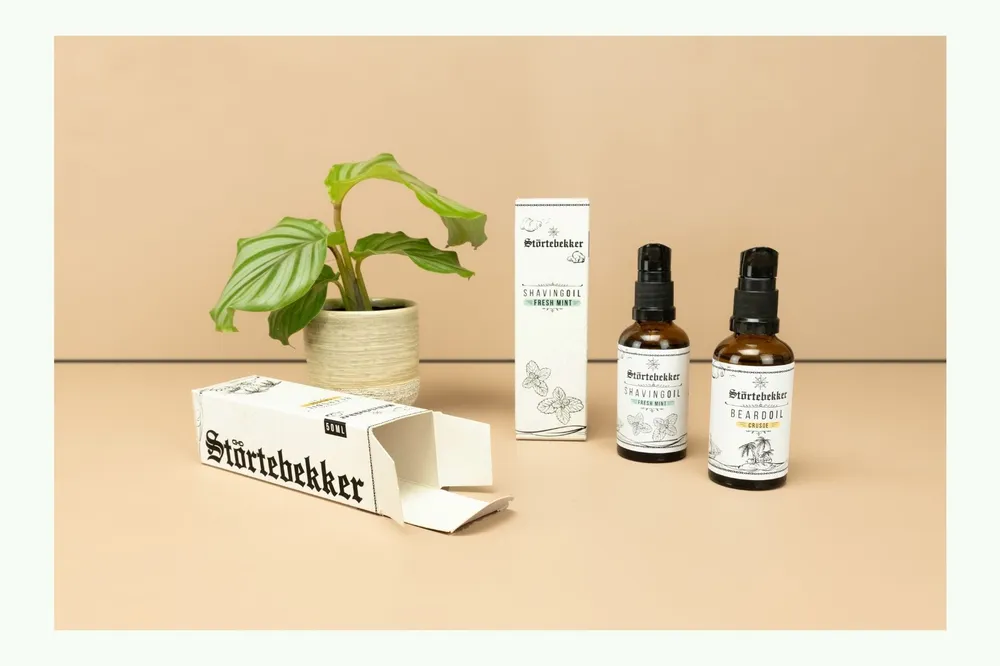
SCHRIFTEN, DIE WIRKEN
Schriften erzählen Geschichten, aber das tun sie nicht nur, indem sie Wörter bilden. Auch jenseits der Informationsebene, die wir für die Kommunikation und Verständigung im Alltag benötigen, haben Schriftarten großen Einfluss auf uns. Die Typografie beschäftigt sich deshalb damit, wie Schriften und ihre Gestaltung auf uns wirken.
Denn jede Schrift hat ihren eigenen Charakter, der bereits in der grundlegenden Form der Buchstaben angelegt ist (Typografen sprechen in diesem Zusammenhang von der Architektur einer Schrift). Damit erzielen verschiedene Schriftarten eine unterschiedliche Wirkung:
Typos, die an Handschriften angelehnt sind und über offene, runde Formen verfügen, empfinden wir als freundlich und warm.
Geometrische, geschlossene Schriften sind mit gegenteiligen Assoziationen verbunden und wirken technisch und kühl.
Breite Buchstaben vermitteln Stabilität, während schmale Schriften einen labilen Eindruck erwecken. Analog dazu können rechte Winkel hart und abgerundete als sanft wahrgenommen werden.
Daneben machen Schriftelemente wie Ober- und Unterlängen einen erheblichen Unterschied, genauso wie eine Betonung der Horizontalen oder Vertikalen:Kurze Ober- und Unterlängen erscheinen bodenständig, sind sie hingegen lang und ausgeprägt, werden sie zu einem Ausdruck von Eleganz.
Liegt der Schwerpunkt einer Schrift auf der horizontalen Ausrichtung, wirkt sie dynamischer, ein Fokus auf der Vertikalen macht sie wiederum statisch.
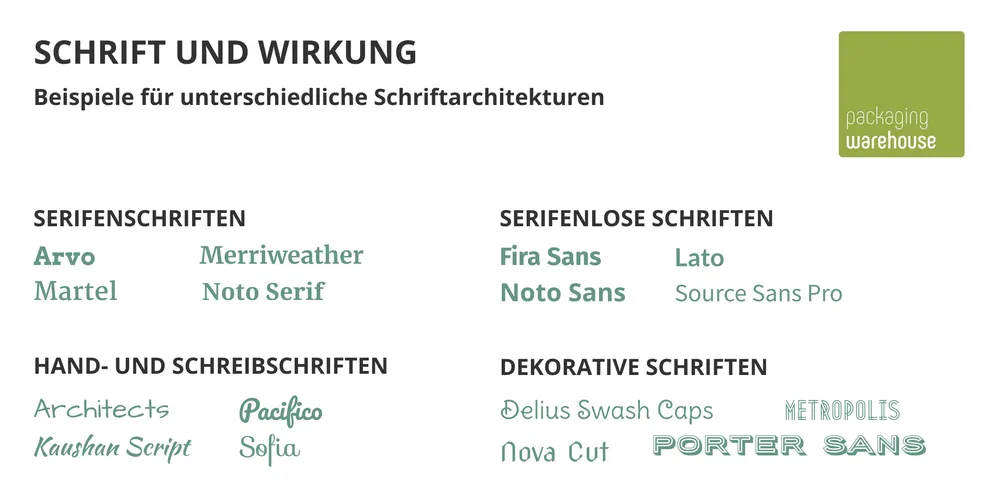
Dazu kommen bestimmte Eigenheiten und besondere Merkmale, die gerade für ein Corporate Design wichtig sind. Auch wenn sie noch so klein sind, können sie einen großen Einfluss auf den Gesamteindruck haben. Mit der Gestaltung von Schrift lässt sich sogar die Bedeutung eines Wortes oder ganzer Inhalte verändern. Und genau wie Formen und Farben wecken Schriftarten bei deinen Kunden bestimmte Emotionen und Assoziationen.
Beim Einsatz von Schrift als gestalterisches Element dreht sich daher alles um die Frage: Wie lassen sich die Eigenschaften und Wirkungen von unterschiedlichen Schriftarten am besten nutzen, um deine Kunden richtig anzusprechen?
SCHRIFT IM VERPACKUNGSDESIGN – EINE TYPENFRAGE
Die oben gestellte Frage lässt sich nur beantworten, wenn du die wichtigsten Schriftartentypen und ihre Eigenheiten kennst.
Serifenschriften
Diese Schriftarten zeichnen sich durch eine kleine Linie am Ende eines Buchstabenstrichs aus – der Serife. Sie sind echte Klassiker und vermitteln auch Klasse. Ihre Wirkung ist dadurch hochwertig und literarisch.
Weil sie so alt und verbreitet sind, ist ihre Form unseren Augen gut vertraut. Das macht Serifenschriften gut lesbar. Für längere Textpassagen und Kleingedrucktes sind sie deshalb eine gute Wahl.
Bekannte Vertreter: Times New Roman
Serifenlose Schriften
Sie sind auch unter dem Begriff „Sans Serif“ bekannt, was nichts anderes bedeutet als „ohne Serifen“. Durch den Verzicht auf die kleinen Füße erscheinen diese Schriftarten modern, klar, sachlich und sauber.
Mit einer Variation der Stärke lassen sich sogar noch mehr unterschiedliche Eindrücke erzeugen: dicke Sans Serif Schriften wirken stark und maskulin, dünne hingegen nobel und glamourös.
Bekannte Vertreter: Helvetica
Schreibschriften
So unverwechselbar wie die eigene Handschrift: Das ist die Idee hinter Schreibschriften und genauso sehen sie aus.
Das Resultat ist eine unglaublich vielfältige Auswahl, die von kalligrafischen Schriften bis zu Typos reicht, die wirklich versuchen Handschriften nachzuahmen. Dabei geht es in erster Linie um ein individuelles, einzigartiges Schriftbild – der repräsentative Aspekt steht hier klar im Vordergrund.
Bekannte Vertreter: Sacramento
Dekorative Schriften
Dekorative Schriften machen aus Buchstaben echte Kunstwerke. Dadurch ist ihre emotionale Wirkung beim Betrachter besonders groß und deshalb kommen sie vor allem als LogoSchriften zum Einsatz. Als Sekundärtext oder für Fließtext sind sie in der Regel zu plakativ – und auch zu schade.